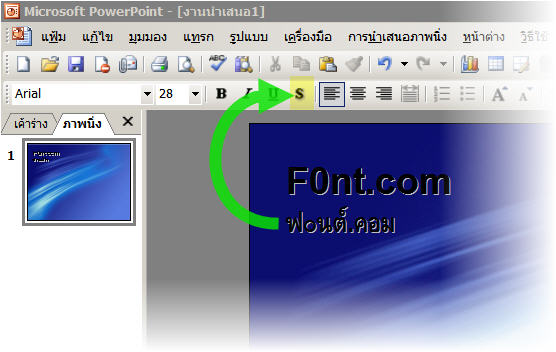
การทำ้เส้นขอบของตัวหนังสือ
ผมเห็นในพวกบรรยายไทยตอนที่ดูหนังอะครับ แล้วนึกขึ้นมาได้ว่า "ไม่ว่าพื้นหลังก็คือหนังจะมีสีอะไร ตัวหนังสือบรรยายไทยก็ยังคงมอง-อ่านออกอยู่" เพราะตัวหนังสือจริงๆมันเป็นสีขาว แต่ขอบๆของตัวหนังสือมีแรเงาสีดำไว้เล็กน้อย เลยทำให้สามารถอ่านตัวหนังสือออกตลอดไม่ว่าจะเป็นฉากสีใด มันมาตรงกับปัญหาที่ผมเจอประจำๆในการทำ powerpoint
ก็คือทุกครั้งที่ผมทำ สีของตัวหนังสือมักจะกลมกลืนกับสีของพื้นหลัง(เพราะภาพพื้นหลังเป็นภาพที่มีลวดลายและสีค่อนข้างมาก) จึงทำให้อ่านตัวหนังสือไม่ออก เลยอยากทราบว่า
จะมี Extension เสริมตัวไหนของ PowerPoint ไหมครับที่ช่วยแก้ปัญหานี้ได้ หรือวิธีไหนบ้าง
คงไม่ได้มั้งครับ
ทำได้มากสุดก็คงเป็นแค่ Word Art แล้วใส่เส้นขอบ
ถ้าให้เป็นตัวหนังสือปกติคงทำไม่ได้ เพราะฟีเจอร์ของ Powerpoint ไปไม่ถึง
ทำแถบสีบางๆ รองตัวหนังสือแบบนี้ได้มั้ย